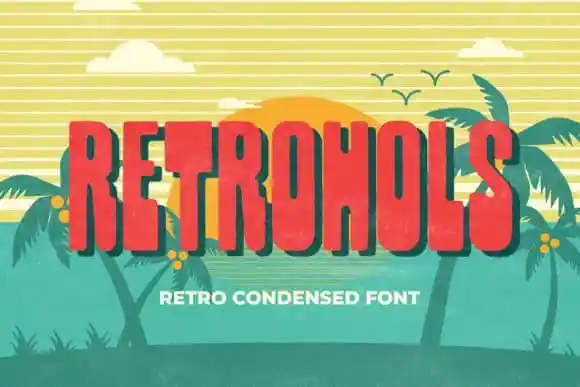
Retrohols Display Font – Fonte Grátis
Retrohols Display Font
Retrohols Display Font é uma fonte criada para enriquecer cada projeto com um toque audacioso e único. Feito à mão, este estilo é perfeito para trabalhos impressos e design de produto. Ideal para usar nas exibições de título e em qualquer idéia de design que possa surgir. Retrohols tem uma sensação leve nostalgia, entregando um encantador visual vintage. Este display font oferece um toque retro especial a qualquer projeto que você imagine. Ele foi criado e compartilhado por almarkhatype. Engajante e versátil, Retrohols é perfeito para quando você quer dar um toque nostálgico ao seu design.